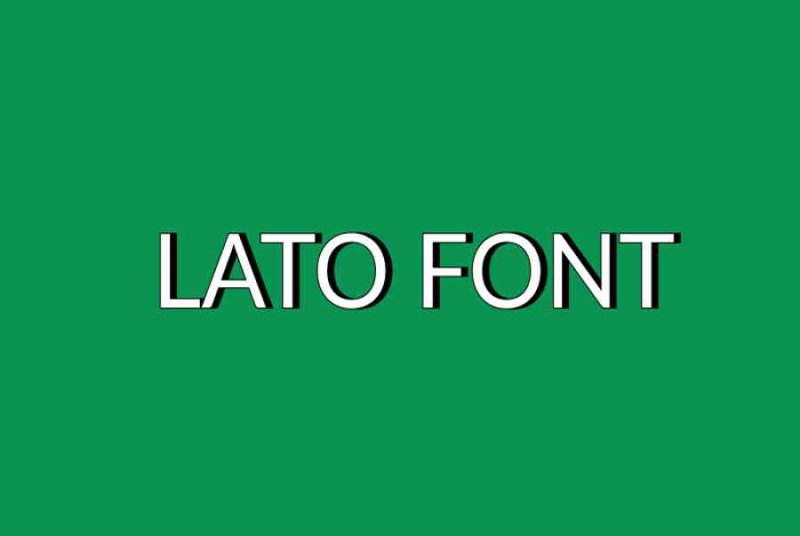
Top 7 Font việt hóa đẹp dành cho dân thiết kế
Font Lato
Lato ( Lato trong tiếng Ba Lan có nghĩa là mùa hè ) là font chữ thuộc họ Sans serif được Łukasz Dziedzic phong cách thiết kế vào mùa hè năm 2010. Sau đó đã được Google tương hỗ xuất bản theo Giấy phép Phông chữ Mở bởi ty Poland .
Font chữ việt Hóa Lato với những đường nét tròn nhẹ trên chữ cái mang lại cảm giác ấm áp của mùa hè nhưng không kém phần sang trọng và nghiêm khắc nhờ vào thiết kế cổ điển.
Font iCielBC Downtown
Font việt hóa này được phong cách thiết kế bởi một bạn nữ TP. Hà Nội, lấy cảm hứng từ những bảng hiệu được vẽ tay, những hình ảnh bình dị, sắc tố đơn thuần từ thời bao cấp. Tuy nhiên font này bạn chỉ nên tải về dùng với mục tiêu cá thể, nếu dùng để phong cách thiết kế thì bạn nên mua bản quyền nhé .
Font SVN-Product Sans
Đây là font chữ Việt Hóa được phong cách thiết kế bởi Google Inc nhằm mục đích mục tiêu thiết kế xây dựng tên thương hiệu cho riêng mình và được dùng để thay thế sửa chữa logo Google vào tháng 9 năm năm ngoái. Bạn sẽ phát hiện font này Open trên hầu hết những ứng dụng của Google .
Font Futura
Futura là một kiểu chữ sans serif được phong cách thiết kế bởi Paul Renner và được phát hành vào năm 1927, dựa trên những hình dạng hình học, đặc biệt quan trọng là hình tròn trụ, giống với niềm tin của phong thái phong cách thiết kế Bauhaus thời kỳ đó. Dù đã sinh ra từ rất lâu nhưng tính đến thời gian hiện tại thì đây vẫn là một trong những font chữ được tìm kiếm phổ cập nhất .
Font Bìa Sách Xưa
Font chữ Bìa Sách Xưa được phong cách thiết kế bởi Tống Văn Diệp, ông đã lấy cảm hứng từ những biển quảng cáo, trên những bìa sách cũ truyền kiếp của Nước Ta vào những năm 1980 của thế kỉ trước. Với đường nét ngang dày và đường nét thẳng dọc mảnh khảnh của từng con chữ gợi lại cảm xúc hoài cổ, hoài niệm cho người đọc .
Font Bon Foyage
Font chữ việt hóa NVN Bon Foyage thuộc họ serif thư pháp theo phong thái tân tiến, tương thích với nhiều chủ đề phong cách thiết kế gồm có thời trang, tạp chí, logo, tên thương hiệu, nhiếp ảnh, lời mời, lời mời đám cưới, trích dẫn, tiêu đề blog, áp phích, quảng cáo, bưu thiếp, sách, website .
Font SVN-TheUntold Story
SVN-TheUntold Story là font chữ viết tay theo phong thái vui nhộn, tinh nghịch. Font chữ này tuyệt vời cho những ấn phẩm phong cách thiết kế gồm có : tờ rơi, thiệp chúc mừng, vỏ hộp mẫu sản phẩm, bìa sách, bìa album, phong cách thiết kế hình ảnh trong may mặc .